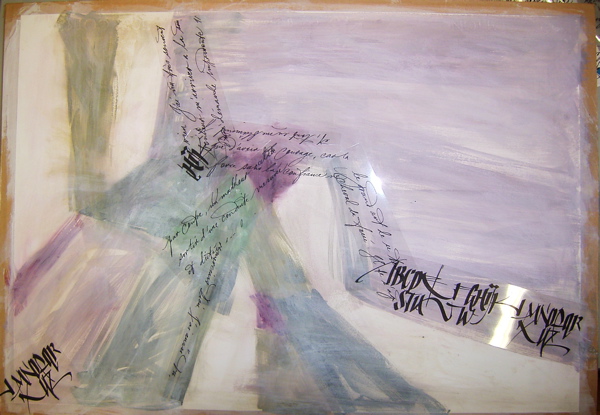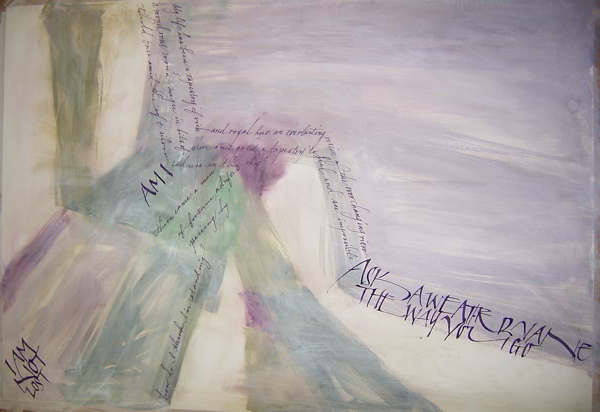
Finding Enjoyment in Writing ³¤
¥¹¥È¥í¡¼¥¯¤Î»Ï¤Þ¤ê¤Ï¤È¤Æ¤âÃí°Õ¿¼¤¯
¡Ä¡£¤³¤ì¤ÏÅÁÅýŪ¤Ê¥µ¥ó¥×¥ë¤Ê¤Î¤Ç¡¢ºÙ¤¤¥é¥¤¥ó¤¬½ñ¤±¤ë¤è¤¦¿´³Ý¤±¤Þ¤¹¡£
L¤Î½Ä¥é¥¤¥ó¤«¤é²£¤ËÆþ¤ë³Ñ¤Ç¤¹¡£
¤³¤ì¤ÏÉԻ׵ĤÊÂθ³¤Ç³Ø¤Ó¤Þ¤·¤¿¡£
¤³¤ÎÆÍµ¯¤Î¤è¤¦¤Ê³Ñ¤ò½Ð¤¹¤Ë¤Ï¡¢
̵Íý¤ä¤êºî¤ë¤Î¤Ç¤Ï¤Ê¤¯¡¢
½Ä¥é¥¤¥ó¤¬²¼¤ê¤¤Ã¤¿½ê¤Ç°ì¸ÆµÛÃÖ¤¤Þ¤¹¡£
¤½¤¦¤¹¤ë¤È¡¢»ý¤Á¼ê¤Î¶ÛÄ¥¤¬´Ë¤ß°ì½Ö¥Ú¥ó¤¬Ìá¤í¤¦¤È¤¹¤ë¤Î¤Ç¤¹¡£ÍÞ°µ¤«¤é²òÊü¤µ¤ì¤Æ
¡Ö¤Õ¤¥¡Á¡£¡×¤Ã¤Æ¸À¤Ã¤Æ¤ë¤ß¤¿¤¤¤Ê´¶¤¸¤Ç¤¹¡£¤Ê¤Î¤Ç¼«Ê¬¤Ç¤ï¤¶¤ÈÌᤷ¤Æ¤Ï¤¤¤±¤Ê¤¤¤Î¤Ç¤¹¡£
¼ÂÁ©¤·¤Æ¤ß¤ë¤ÈÉԻ׵Ĥʵ¤»ý¤Á¤Ë¤Ê¤ê¤Þ¤¹¡£¡Ö¤¢¡Á¼«Á³¤Ë¤³¤Î·Á¤Ë¤Ê¤ë¤ó¤À¡Á¡×¤È¡£
¤½¤·¤Æ³Ñ¤Ï90Å٤ǤϤʤ¯¡¢¤â¤¦¤ï¤º¤«¤Ç¤¹¤¬90ÅÙ¤è¤ê¹¤¤¤Î¤Ç¤¹¡£¤½¤¦¤¤¤¦¸«¤¨¤ë¤«¸«¤¨¤Ê¤¤
¤¯¤é¤¤¤Î¹¤¬¤ê¤¬ÌܤËÍ¥¤·¤¤¤½¤¦¤Ç¤¹¡£
¤³¤ÎL¤ò½ñ¤¯ÍͻҤòEwan¤Ï¸ÀÍÕ¤Çɽ¸½¤·¤Æ¤¯¤ì¤Þ¤¹¡£
¡ÖÃØé᤬¾å¤Ã¤Æ¡¢¥¹¡¼¤È»å¤ò¿â¤é¤·¤Æ²¼¤ê¤Æ¤¯¤ë¡£»ß¤Þ¤Ã¤Æ¡Ä¥¹¥¿¥¹¥¿¡Äƨ¤²¤ë¡×¤ß¤¿¤¤¤Ê¡Ä¡£¡Ê¾Ð¡Ë
¤½¤ì¤òƬ¤ÇÉÁ¤¤Ê¤¬¤é½ñ¤¯Îý½¬¤ò¤·¤Þ¤¹¡£¤¹¤ë¤È¤È¤Æ¤â¿´ÃϤ褤¥ê¥º¥à¤Ç½ñ¤±¤ë¤Î¤Ç¤¹¡£
U¤Ï¡¢º¸Â¦¤ò½ñ¤¤¤Æ±¦¤ò½ñ¤¯¤È¤¡¢°ìËÜÄ´»Ò¤Ç½ñ¤¤Þ¤»¤ó¡£
±ß¤òÆâºß¤¹¤ëʸ»ú¤ÈƱ¤¸¤è¤¦¤Ë¶õÃæ¤Ç¥«¡¼¥Ö¤òÉÁ¤¤Ê¤¬¤é
±¦Â¦¤Î»Ï¤á¤ËÆþ¤ê¤Þ¤¹¡£
U¤ÎÃæ¤Î¶õ´Ö¤Ë¤â¥¨¥Í¥ë¥®¡¼¤¬Æþ¤ê¹þ¤à¤ó¤Ç¤¹¤Í¡Ä¡£
¤¹¤´¡Á¤¤¡£
¤³¤ì¤â¾×·â¡Ä¡£
V,W,M¤Ê¤É¤Î¸òº¹¤¹¤ëÉôʬ¤Ç¤¹¡£
¤³¤Î½Å¤Ê¤ê¤¬¤¦¤Þ¤¯¤¤¤«¤Ê¤¤¤È¡¢¥Ü¥Ã¥Æ¥ê¤Ê¤³¤È¤Ë
¤Ê¤Ã¤Æ¤·¤Þ¤¤¤Þ¤¹¤Í¤§¡Ä¡ÊÎÞ¡Ë
¤³¤ì¤Ïº¸¤«¤é¤¯¤ë¥¹¥È¥í¡¼¥¯¤ÎºÇ¸å¤Ë¤ï¤º¤«¤Ë
º¸¤Ø¤Ï¤é¤¦¤È¤¤¤¦¤«¤Ï¤Í¤ë¤È¤¤¤¦¤«¡Ä¡£
¤³¤¦¤¹¤ë¤í±¦¤«¤é¤Î¥¹¥È¥í¡¼¥¯¤¬½Å¤Ê¤Ã¤¿¤È¤¤Ë¡¢
¥·¥ã¡¼¥×¤Ê·Á¤¬ÊݤƤ뤽¤¦¤Ç¤¹¡£
Ewan¤Ï¡¢Ann Camp¤Î¶µ¤¨»Ò¤Ç¤¹¤«¤é¡¢Ann¤Î¥×¥í¥Ý¡¼¥·¥ç¥ó¤Ç¶µ¤¨¤Æ¤¯¤ì¤Þ¤¹¡£
¤¿¤¤¤Æ¤¤¤Ï¡¢Sheila¤ÎÊýË¡¤Ç¡¢ÀµÊý·Á¤ÎÃæ¤Ë±ß¤ò½ñ¤¡¢¤½¤ÎÀµÊý·Á¤ËÂгÑÀþ¤ò°ú¤¡¢±ß¤Î¸Ì¤È¸ò¤ï¤ë½ÄÀþ¤¬Ä¹Êý·Á¡ÊA¤È¤«H¤È¤«¡Ë¥°¥ë¡¼¥×¤È¤Ê¤ê¡¢ÈæÎ¨¤ÏÁ´ÂΤλÍʬ¤Î»°¤Ë¤Ê¤ê¤Þ¤¹¤¬¡¢Ann¤Ï¡¢
±ß¤òÀè¤Ë½ñ¤¯¤ó¤Ç¤¹¤Í¡Ä¡£¿Þ¤Ë½ñ¤«¤Ê¤¤¤È¤ï¤«¤ê¤Ë¤¯¤¤¤Î¤Ç¤¹¤¬¡¢±ß¤ò¤«¤¤¤ÆÄ¹Êý·Á¤Ç°Ï¤à¤Î¤Ç¡¢
ĹÊý·Á¤ÎÈæÎ¨¤¬»Íʬ¤Î»°¤è¤ê¾¯¤·¹¤¯¤Ê¤ë¤Î¤Ç¤¹¡£¤Þ¤¡¤³¤ì¤Ï¹¥¤ß¤Ë¤â¤è¤ê¤Þ¤¹¤Í¡£
¡Ê¤³¤ÎÈæÎ¨¤Îº¹¤Ï¡¢nib¤ÎÂÀ¤µ¤Ç±Æ¶Á¤·¤Æ¤¤Þ¤¹¡£¡Ë
¤Ç¤â°ìÈÖ¤ÎÂé¸ïÌ£¤Ï¡¢Ewan¤¬Ê¹¤¤¤¿Ïä·¤«¤é¤Î¹½Â¤¤Î³Ø¤ÖÊýË¡¤Ç¤¹¡£
Ê©Áü¤ÎÉÁ¤Êý¤ò¶µ¤¨¤ëÊýË¡¤Î°ì¤Ä¤Ë¡¢¿ÈÂΤΥѡ¼¥Ä¤ò¼è¤ê¹þ¤ó¤À»í¤ò°Åµ¤¹¤ë¤³¤È¤Ç
³Ð¤¨¤ëÊýË¡¤¬¤¢¤ë¤ó¤À¤½¤¦¤Ç¤¹¡£¤½¤³¤«¤é´ö²¿³Ø¤Ç³Ð¤¨¤ë¤À¤±¤Ç¤Ï¤Ê¤¤ÊýË¡¤òEwan¤â
¸«¤Ä¤±¤¿¤Î¤À¤½¤¦¤Ç¤¹¡£
ÀΤν¤Æ»±¡¤Ç¤âʸ»ú¤Î¹½Â¤¤òÀâÌÀ¤·¤Æ¤¤¤ë»í¤¬¤¢¤Ã¤¿¤½¤¦¤Ç¤¹¡£
¤½¤¦¤¤¤¦¤â¤Î¤ò¸«¤Ä¤±¤Æ¡¢Ewan¼«¿È¤¬³Æ¥¢¥ë¥Õ¥¡¥Ù¥Ã¥È¤Î¥¹¥È¡¼¥ê¡¼¤òºî¤ì¤ë¤è¤¦¤Ë¤Ê¤Ã¤¿
¤½¤¦¤Ç¤¹¡£
¡ÖW¡×¤ò½ñ¤¯¤È¤¤Î¤ªÏ䷤Ǥ¹¡£
1. Dusk 2.pink evening 3. an ink-stroke pine 4. a single star
¤µ¤¡¡¢¤³¤Î1¡Á4¤ÏW¤Î½ñ¤½ç¤Ç¤â¤¢¤ê¤Þ¤¹¡£¤³¤Î1¡Á4¤Î¸ÀÍÕ¤ò»×¤¤¤Ê¤¬¤éW¤ò½ñ¤¤¤Æ
¤ß¤Æ¤¯¤À¤µ¤¤¤Í¤§¡£
1¤¿¤½¤¬¤ì¤Î¥¹¥È¥í¡¼¥¯¡¢2ͼ¾Æ¤±¤¬Èþ¤·¤¤¥¹¥È¥í¡¼¥¯¡¢3ͼ¾Æ¤±¤¬°Å¤¯¤Ê¤ê±Æ¤À¤±¤¬Â¸ºß
¤·¤Æ¤¯¤ë¥¹¥È¥í¡¼¥¯¡¢4¸÷¤¬¸«¤¨¤ë¡Ä¸÷¤Ï¤À¤ó¤À¤ó²¼¤ê¤Æ¤¯¤ë
»þ´Ö¤Þ¤Çή¤ì¤Æ¤¤¤Þ¤¹¤Í¤§¡£
¤³¤ó¤ÊÉ÷¤Ë´¶¾ð¤ò¹þ¤á¤Ê¤¬¤éʸ»ú¤òÎý½¬¤Ç¤¤¿¤éËÜÅö¤Ë³Ú¤·¤¤¤Ç¤¹¤Í¤§¡ª
¤½¤·¤Æ¡¢¸åȾ»°Æü´Ö¤Îh¤Ï¡¢µã¤Ã¥ê¥°¥é¥Õ¥¡¡¼¤Ë¤Ê¤ê¤Þ¤·¤¿¡£
¤Þ¤¿¸åÆü¡Ä¡£
Finding Enjoyment in Writing
mojitor-s¤µ¤ó¤¬¿§¤Ç¥¥ã¥Ï¥¥ã¥Ï&¥¦¥ë¥¦¥ë¤·¤Ê¤¬¤é¤â¡¢
ÁÇÀ²¤é¤·¤¤»ØÆ³¤ò¤·¤Æ¤¤¤ë¤ªÎÙ¡Ä¡£
mojitor-h¤Ï¡¢½ñ¤¤¤Æ¤Þ¤·¤¿¡Ä¡£¡¦¡¦¡¦¤«¡¦¤¡¦¤¿¡¦¤¤¡¦¡ª
º£²óKLAS¤ÎWS ¤Ç¤Ï¡¢Á°È¾¡¢¸åȾ¤È¤âEwan¤Î¥¯¥é¥¹¤ò¼õ¹Ö¡£
ºÇ¶á¤æ¤Ã¤¯¤ê¤È½ñ¤¯»þ´Ö¤â̵¤¯¡¢¤³¤ÎÆü¤ò¿´ÂÔ¤Á¤Ë¤·¤Æ¤¤¤¿¤Î¤Ç¤·¤¿¡£
¡ÖFinding Enjoyment in Writing¡×¡¦½ñ¤¯³Ú¤·¤µ¤ò¸«¤¤¤À¤¹¡¦
Ewan¤¬½é¤á¤ÆÍèÆü¤·¤Æ¤«¤é4ÅÙÌܡʤ½¤Î´Ö10ǯ¡Ë¡¢Ëè²óEwan¤¬
¶µ¤¨¤¿¤¤º¬¤Ã¤³¤ÏÊѤï¤ê¤Þ¤»¤ó¡£
ʸ»ú¤ò½ñ¤¯¤È¤¤Ï¡¢Á´¤Æ¤Î¤³¤È¤Ë¼ª¤ò·¹¤±¡¢¸«¤Ä¤á¡Ä´¶¤¸¤ë¤³¤È¡Ä¡£
ºÇ½ª·ë²Ì¤Ç¤Ï¤Ê¤¯¡¢¡Ö½ñ¤¯¡×¤È¤¤¤¦¹Ô°Ù¤½¤Î¤â¤Î¤ò³Ú¤·¤ß¡¢´î¤Ó¤ò
¸«¤Ä¤±¤ë¤³¤È¡Ä¡£¥í¡¼¥Þ¥ó¥¥ã¥Ô¥¿¥ë¤ò½ñ¤¤Þ¤¹¤¬¡¢´ö²¿³Ø¤Ç½ñ¤¤¤Á¤ã¤¢¤¤¤±¤Þ¤»¤ó¤¾¡Ä¡£¥¤¥ó¥Ê¡¼¥¹¥Ú¡¼¥¹¤Ï¤¿¤À¤Î¶õÇò¤¸¤ã¤Ê¤¤¤ó¤Ç¤¹¤è¡ª¤½¤ÎÃæ¤Ï¤É¤Ã¤·¤ê¤·¤Æ
¥¨¥Í¥ë¥®¡¼¤¬Ëþ¤¿¤µ¤ì¤Æ¤ë¤ó¤Ç¤¹¤è¡ª
»ä¤¿¤Á¤¬½ñ¤¤¤Æ¤¤¤ëÀþ¤Ïư¤¤¤Æ¤¤¤Þ¤¹¤Í¡Ä¡£Á´¤Æ¤Îư¤¤Ë¤Ï´¶¾ð¤¬¹þ¤á¤é¤ì¤Æ¤¤¤Þ¤¹¡£
¤½¤Îư¤¤«¤é¥¯¥ê¥¨¥¤¥È¤µ¤ì¤¿¤â¤Î¤¬Calligraphy¤Ê¤ó¤Ç¤¹¤è¡£¤½¤ì¤Ï¿¹ÍåËü¾Ý¤ÎÀ¤³¦¤«¤é³Ø¤Ö
¤â¤Î¤Ê¤ó¤Ç¤¹¤è¡Ä¡£
¤½¤Îư¤¤ò¥Þ¥¹¥¿¡¼¤¹¤ë¤Î¤Ë¤Ï¡©
ư¤¤ò¼ÙË⤹¤ë¤â¤Î¤¬¤¤¤í¤¤¤í¤¢¤ê¤Þ¤¹¡£
¡Ö¥¥ã¡¼¡×¤ª¾î¤µ¤ó¡ª¼«Ê¬¤Î½ñ¤¤¤¿Àþ¤ò¤³¤ó¤Ê¤ËÀܼ̤·¤¿¤³¤È¤¬
¤¢¤ê¤Þ¤¹¤«¡©ÌÓ·ê¤âÉݤ¤¤¬¤³¤ì¤âÉݤ¤¡Ä¡£
°ì¿Í¡¢°ì¿Í¡¢»Ø¤ÎŤµ¤â°ã¤¦¤·¡¢Êʤ⤢¤ë¡Ä¡£
¤â¤·¡¢¤¢¤Ê¤¿¤¬¤³¤Î¤è¤¦¤ËÀþ¤Îº¸Â¦¤¬¥®¥¶¥®¥¶¤·¤Æ¤¤¤¿¤é¡¢
»Ø¤ÎÎϤΥХé¥ó¥¹¤¬Êø¤ì¤Æ¤¤¤ë¾Úµò¤Ç¤¹¡£
¿Æ»Ø¤è¤ê¤Ò¤È¤µ¤·»Ø¤ÎÎϤÎÊý¤¬¶¯¤¤¤Î¤Ç¤¹¡£¤³¤ì¤Ëµ¤¤Å¤¤¤¿¤é
ξ»Ø¤ÎÎϤò¶ÑÅù¤Ë¤Ê¤ë¤è¤¦¤Ë¿´¤¬¤±¤Þ¤·¤ç¤¦¡ª
¤â¤·¤«¤·¤¿¤é»ÑÀª¤¬°¤¤¤Î¤«¤â¤·¤ì¤Þ¤»¤ó¡Ä¡£´ù¤Î¹â¤µ
¹ç¤Ã¤Æ¤Þ¤¹¤«¡©Î¾Â¤Ï¤Á¤ã¤ó¤È¾²¤Ë¤Ä¤¤¤Æ¤Þ¤¹¤«¡©
°Ø»Ò¤Ë¤Ï¤Á¤ã¤ó¤È¿¼¤¯ºÂ¤Ã¤Æ¤Þ¤¹¤«¡©
Ewan¤Ï°ì¿Í¤º¤Ä½ñ¤¤¤Æ¤ë»Ñ¤ò¼Ì¿¿¤Ë»£¤ê¡¢¤É¤³¤Ëµ¤¤ò¤Ä¤±¤ë¤«¥¢¥É¥Ð¥¤¥¹¤·¤Æ¤¯¤ì¤Þ¤·¤¿¡£
¤ªÎÙ¤ÎK¤µ¤ó¡ª¤´¶¨ÎϤ¢¤ê¤¬¤È¤¦
¤´¤¶¤¤¤Þ¤¹¡£¡Ê¾¡¼ê¤Ë¡Ä¡Ë
´ù¤¬¾¯¤·¹â¤¤¤Î¤Ç°Ø»Ò¤ò¤â¤¦°ì¤Ä
½Å¤Í¤ÆÄ´À°¤·¤Þ¤¹¡£¤½¤¦¤¹¤ë¤È¤¬
É⤯¤Î¤Ç¡¢¿·Ê¹»æ¤òÉߤ¤¤ÆÂ¾ì¸Ç¤á¡ª°Ø»Ò¤â¿¼¤á¤ËºÂ¤Ã¤Æ°ÂÄꤷ¤Æ¤¤¤Þ¤¹¤Í¡£
¤½¤¦¤¹¤ë¤È¡¢¤É¤¦¤Ç¤·¤ç¤¦¡Á¡£±¦ÏӤμê¼ó¤«¤éɪ¤Þ¤ÇÃúÅÙÎɤ¤Ä¹¤µ¤Ë¤Ê¤ê¤Þ¤·¤¿¡£Ã»¤¹¤®¤ë¤È¡¢
¼ê¤ÎưºîÈϰϤ¬¶¹¤Þ¤ê¤Þ¤¹¡£Ä¹¤¹¤®¤ë¤È¼ê¤ËÎϤ¬¤¦¤Þ¤¯ÅÁ¤ï¤ê¤Þ¤»¤ó¡£»æ¤Î¾å¦¤Ë¤Ï²¿¤«Êª¤ò
ÃÖ¤¤¤Æ¤Ï¤¤¤±¤Þ¤»¤ó¤è¡ª¾ï¤Ë¼«Ê¬¤¬½ñ¤¯¤â¤Î¤ÎÃæ¿´¤Ë¤¤¤ë¤³¤È¤Ç¤¹¡ª
¤è¤¯°Ø»Ò¤ËÀõ¤¯ºÂ¤ë¿Í¤¬¤¤¤Þ¤¹¤¬¡¢¤³¤ì¤Ï´ù¤¬¹â¤¹¤®¤ë¤«¤é¡¢¼«Ê¬¤¬Á°¤ÎÊý¤Ë¤º¤é¤·¤ÆºÂ¤Ã¤Æ
¤È¤¤¤¦¤ï¤±¤Ç¡¢¥Ö¥í¥Ç¥£¤¬²ò·è¤·¤Æ¤¯¤ì¤¿¤ª¤«¤²¤Ç
¤µ¡Á¤Æ¡¢¤³¤³¤«¤é¤É¤¦¤ä¤Ã¤Æ¤ß¤Þ¤·¤ç¤¦¤«¤Í¡Á¡£
¼ºÇÔ¤ò¶²¤ì¤º¤ËÆÍ¤¿Ê¤á¡Á¡ª¤Ç¤¹¤Í¡©¡ª
¤È¤³¤í¤Ç¡¢¤³¤ÎºîÉʤΥơ¼¥Þ¤Ï¤Ç¤¹¤Í¡¢¡Ö¹Ô¤¯¤Ù¤Æ»¤ÏÉ÷¸«·Ü¤Ëʹ¤±¡×¡Ö»ä¤Ï̤ï¤Ê¤¤¡¦¡¦¤«¡©¡×¤È¤¤¤¦¡¢¤Ü¤ó¤ä¤ê¤·¤¿É԰¤ȥե饹¥È¥ì¡¼¥·¥ç¥ó¤È¤Ê¤ó¤È¤«½ÐÍ褿°Â¿´´¶¤È¤ä¤ê¿ë¤²¤¿¤Á¤ç¤Ã¤È¤Ð¤«¤ê¤Î¼«¿®¤È¿ÍÀ¸¤É¡¼¤Ë¤«¤Ê¤ë¤µ¤ÎÆþ¤ê¸ò¤¸¤Ã¤¿¤â¤Î¡¡¤Ê¤Î¤Ç¡¦¤·¡¦¤¿¡ª
Ê£»¨²á¤®¡Á¡ª¡©